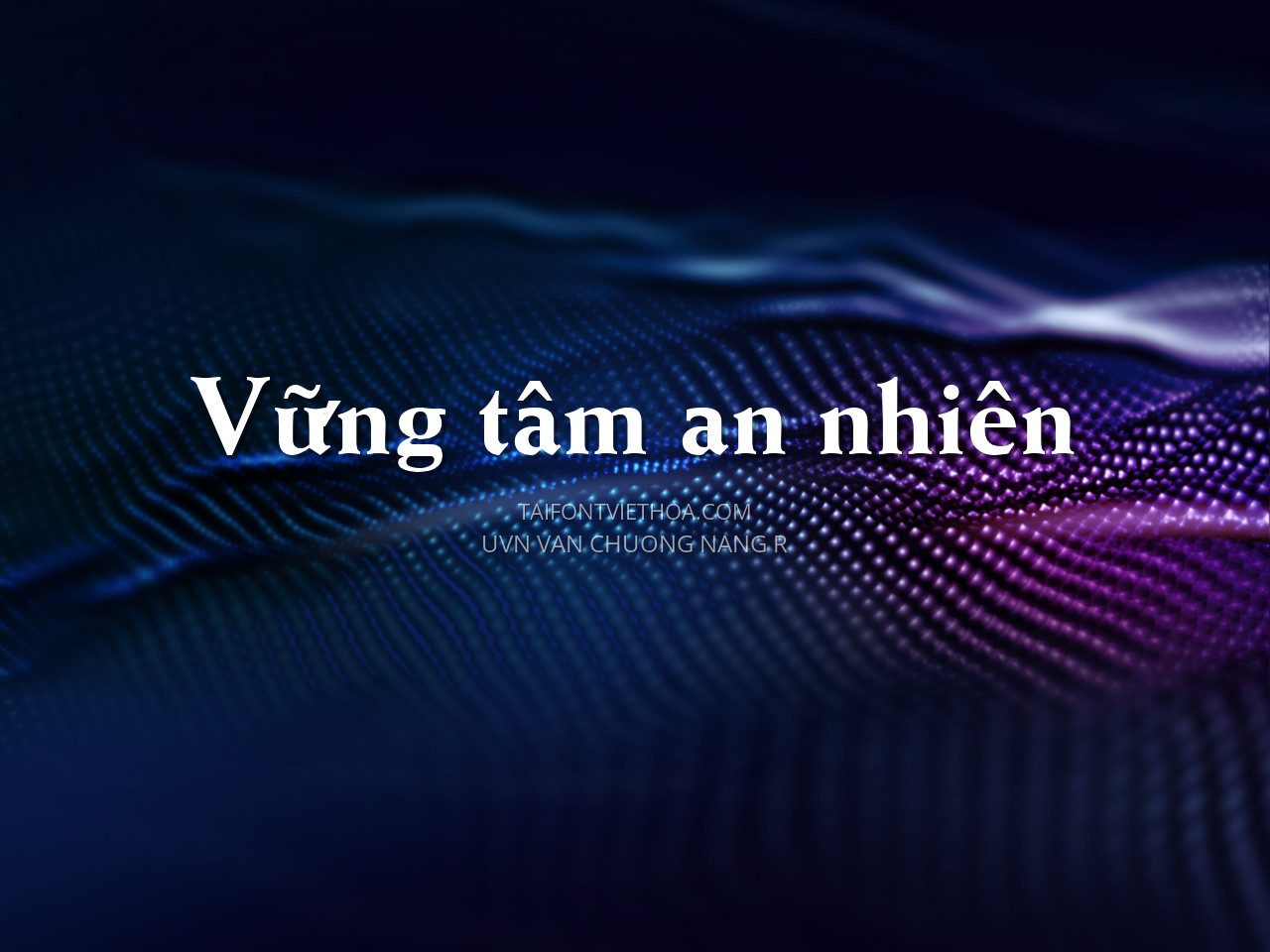
Giới thiệu về font UVN Van Chuong Nang
UVN Van Chuong Nang là phiên bản đậm hơn của bộ font UVN Van Chuong, mang lại cảm giác mạnh mẽ và nổi bật hơn trong các thiết kế học thuật và văn hóa. Với phong cách cổ điển pha chút hiện đại, font này giúp truyền tải các nội dung văn chương, giáo dục một cách rõ ràng, trang trọng nhưng vẫn giữ được vẻ gần gũi, truyền cảm. UVN Van Chuong Nang được sưu tầm và chia sẻ bởi thành viên Font Chuẩn, và hiện được taifontviethoa.com sử dụng trong các dự án thiết kế bìa sách, tài liệu học đường và các ấn phẩm văn hóa mang giá trị lâu dài.
Đặc điểm thiết kế và ứng dụng của UVN Van Chuong Nang
Font UVN Van Chuong Nang giữ nguyên cấu trúc serif mềm mại, với các chân chữ thanh lịch và các nét chữ được làm đậm hơn để tăng độ tương phản và khả năng hiển thị. Sự kết hợp giữa nét cổ điển và độ đậm hiện đại giúp font nổi bật trong những bối cảnh cần tạo điểm nhấn hoặc tiêu đề mang tính học thuật. Font hỗ trợ đầy đủ tiếng Việt và lý tưởng cho các ứng dụng truyền thông văn hóa hoặc tài liệu chuyên đề.
Ứng dụng lý tưởng: bìa sách văn học, tiêu đề giáo án, poster triển lãm văn hóa, thiết kế brochure cổ điển. Ngành nghề phù hợp: giáo dục, xuất bản, văn hóa truyền thống, sự kiện nghệ thuật và thiết kế học thuật.